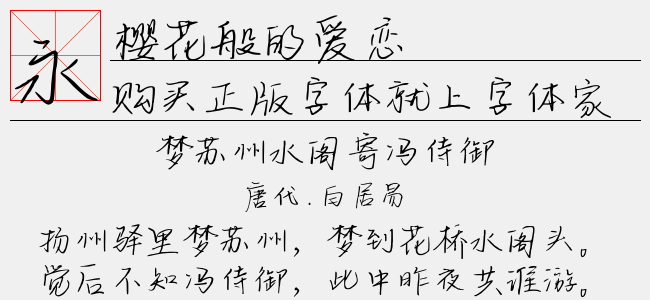
樱花般的爱恋
字体作者:三极字库
字体名称:樱花般的爱恋
字体家族:三极系列
书体类型:手写体/拼音
字体公司:三极字库
樱花般的爱恋
樱花般的爱恋是一款不错的艺术字体,由Aa字库出品,字体笔触适中,字形端正,具有很好的视觉感,适合应用于艺术设计、平面宣传设计、网页设计,书法字帖等领域,需要的朋友可以前来本站下载。